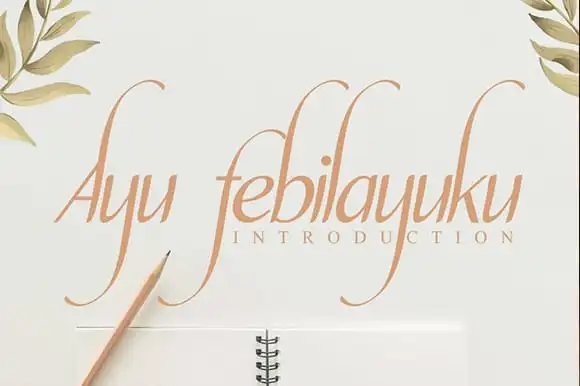
Ayu febilayuku Calligraphy Font – Download Grátis
Ayu febilayuku é uma bela calligraphia que se destaca entre as outras fontes. Com traços finos e sutis, ela oferece um toque elegante para qualquer projeto gráfico. Aproveite sua natureza suave e elegante tanto no design de papel quanto em criações digitais como postagens nas redes sociais ou identidade visual da sua marca. A fonte também se adapta perfeitamente a embalagens, logotipos de produtos, marcadores, etiquetas e até mesmo para o texto do seu site. Suas linhas delicadas criam um contraste harmonioso, tornando-se uma escolha óbvia para aqueles que desejam personalidade em seus projetos. Essa fonte é perfeita tanto para trabalhos comerciais quanto pessoais, oferecendo uma textura única e autêntica. Com seu design suave e delicado, Ayu febilayuku se destaca como a fonte ideal para aqueles que buscam um touch de elegância em seus projetos. Seja você um designer gráfico profissional ou simplesmente alguém que busca um toque único em suas criações digitais e físicas, essa fonte é uma escolha inteligente. Seu estilo perfeito para a sua personalização artesanal, ela se torna o ponto de brilho em qualquer projeto gráfico. Em suma, Ayu febilayuku é uma fonte que não apenas complementa seu trabalho, mas também o eleva a um nível superior.